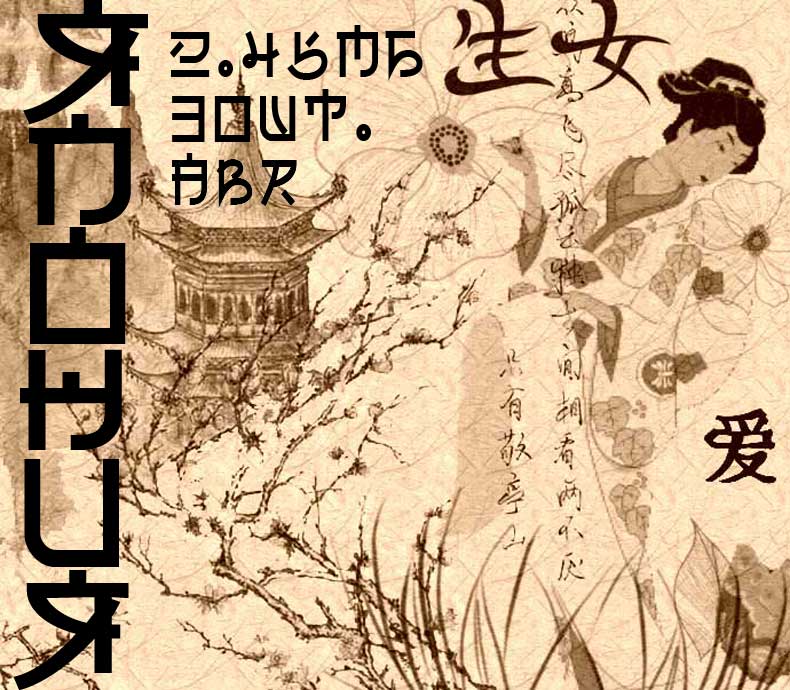
Русско-китайская транслитерация
В чужом языке всегда ищещь что-то знакомое. В китайском попадаются иероглифы, похожие на русские или английские буквы. Как-то раз я собрался и, просмотрев около 10 тысяч иероглифов, подобрал наиболее похожие на русский алфавит. В таблице были лакуны, но на известном портале Восточное Полушарие мне помогли подобрать недостающие иероглифы.
Результатом стала таблица замен и сервис замены русских букв на иероглифы. Этакая транслитерация с русского на китайский. Практическое назначение у нее исключительно развлекательное. Подпись там стилизованную под Китай сделать для блога или форума. Или вывеску.
Правда, стоит иметь в виду, что в отличие от практической транскрипции, где иероглифы не означают ничего и несут только звучание, эти иероглифы означают слова, а их комбинация может быть осмысленной фразой.
Таблица замен (по ссылке перевод из БКРС-онлайн)
А: 闩
Б: 石
В: 乃
Г: 厂
Д: 亼
Е: 仨
Ё: 仨
Ж: 水
З: 弓
И: 认
Й: 认
К: 片
Л: 人
М: 爪
Н: 卄
О: 口
П: 冂
Р: 卩
С: 匚
Т: 丅
У:
Ф: 中
Х: 乂
Ц: 凵
Ч: 丩
Ш: 山
Щ: 山
Ъ: 乙
Ы: 辷
Ь: 乙
Э: 彐
Ю: 扣
Я: 牙
Нужно ли использовать кавычки для цитирования китайских шрифтов?
Вам не нужно делать следующее:
семейство шрифтов: Georgia, «Times New Roman», «Microsoft YaHei», «Microsoft YaHei», STXihei, «Chinese Fine Black», засечки;
Вам следует сделать это:
семейство шрифтов: Georgia, Times New Roman, Microsoft YaHei, STXihei, китайский мелкий черный, с засечками;
Основные китайские шрифты
Песня Ti No. 12 — ШРИФТ SIMSUN 12PT
семейство шрифтов: Arial, Helvetica, tahoma, verdana, Arial, SimSun, китайский мелкий черный, STXihei, без засечек;
Microsoft Yahei — MICROSOFT YAHEI
семейство шрифтов: Tahoma, Arial, Helvetica, «Microsoft YaHei New», «Microsoft Yahei», «Microsoft Yahei», Times New Roman, SimSun, STXihei, «Chinese Fine Black», без засечек;
Имитация песни — FANGSONG
семейство шрифтов: Georgia, «Times New Roman», «FangSong», «Имитация песни», STFangSong, «Китайская имитация песни», с засечками;
Kaiti-KAITI
семейство шрифтов: Georgia, «Times New Roman», «KaiTi», «kaiTi», STKaiti, «Chinese KaiTi», с засечками;
Обработка китайского @ FONT-FACE?
Учитывая, что многие файлы китайских шрифтов очень большие и содержат не менее 3000 основных глифов, поддержка китайского языка для @ font-face не очень хорошая.
Вы можете читать, редактировать и корректировать кириллические тексты, даже если у вас На компьютере нет файлов кириллических шрифтов или поддержки кодовых страниц. А кириллица поддержка необходима для правильной обработки экспортируемого текста.